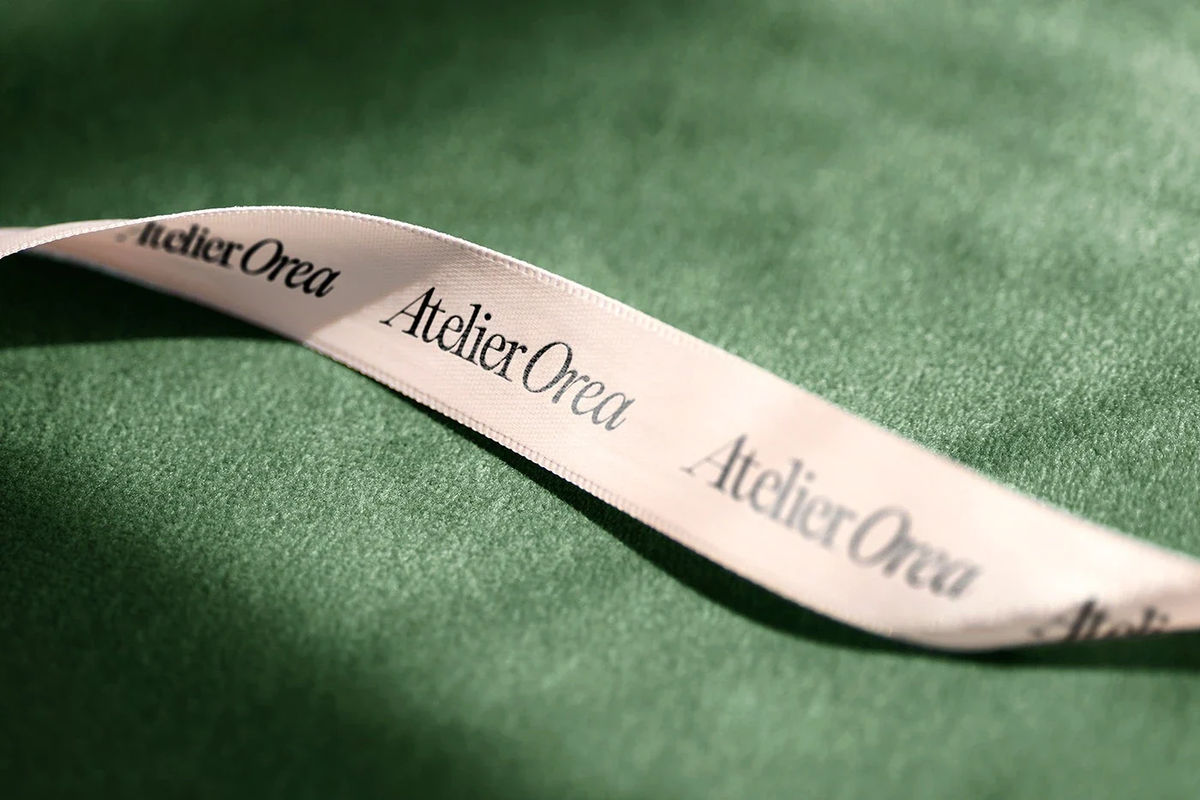
La bonne typographie transmet l'héritage, le savoir-faire et l'exclusivité à travers l'emballage, l'image de marque et chaque détail raffiné.
Des logotypes discrets aux textes d'emballage méticuleusement espacés, chaque choix typographique contribue à un sentiment d'exclusivité. Contrairement aux industries axées sur les tendances, le luxe opère sur la longévité et la cohérence. La typographie s'appuie souvent sur des formes intemporelles, puisant dans des références classiques tout en conservant une touche contemporaine. Les sérifs à fort contraste, les sans-sérifs élégants et les formes de lettres soigneusement ajustées contribuent à créer un langage visuel qui se veut à la fois raffiné et durable, à travers les emballages, les certificats, les environnements de vente au détail et les expériences numériques.
Museum
Museum apporte un équilibre sophistiqué entre élégance classique et caractère contemporain. Ses formes raffinées en font un choix solide pour les identités de luxe qui veulent paraître établies sans devenir prévisibles. Utilisée de manière proéminente, Museum peut rendre un mot-symbole ou un titre immédiatement reconnaissable. Utilisée plus subtilement, elle ajoute du raffinement à la typographie de support et aux communications de la marque.
Eiko
La typographie de luxe s'inspire souvent de la conception de caractères traditionnelle, et Eiko embrasse cet héritage avec un caractère contemporain très expressif. Les formes de lettres distinctives d'Eiko apportent un sentiment d'art et de drame à l'image de marque, ce qui la rend particulièrement efficace pour les produits où la beauté et l'artisanat sont au cœur de l'histoire de la marque. Ses détails brillent à des tailles plus grandes, ce qui la rend particulièrement adaptée aux emballages de parfums, aux campagnes de mode, aux bijoux, aux mises en page éditoriales et aux mots-symboles de luxe.
Watch
Le luxe moderne s'est considérablement étendu au-delà des maisons de couture traditionnelles. La technologie, l'aménagement intérieur, le style de vie, le design et les marques de mode contemporaines opèrent de plus en plus dans l'espace premium. Leur typographie doit communiquer la qualité tout en restant actuelle. Watch peut offrir cet équilibre. Son caractère raffiné fonctionne à travers les logos, les titres, les emballages, les expériences numériques, les campagnes et les environnements de vente au détail, aidant à créer une identité visuelle cohérente à travers les points de contact physiques et numériques.
Editorial Old
Editorial Old est un choix naturel pour les marques qui veulent communiquer l'élégance, l'héritage et la narration. Son caractère sophistiqué se prête aux campagnes de mode, à l'image de marque de la beauté, aux lancements de parfums et aux mises en page éditoriales. Il peut donner à l'histoire d'un produit l'impression d'une double-page de magazine soigneusement mise en scène, transformant la typographie en un élément important de l'image de marque.
Pangaia
Pangaia adopte une approche plus classique de la typographie de luxe. Plutôt que de s'appuyer fortement sur des références contemporaines, elle reflète un retour conscient du design à l'image de marque premium traditionnelle. Le caractère de Pangaia la rend bien adaptée à une nouvelle génération de marques de luxe cherchant à conserver une touche traditionnelle avec une touche contemporaine. Elle peut être utilisée pour les emballages, les sites web, les campagnes, les espaces de vente au détail et les expériences numériques tout en conservant un langage visuel clair et reconnaissable.